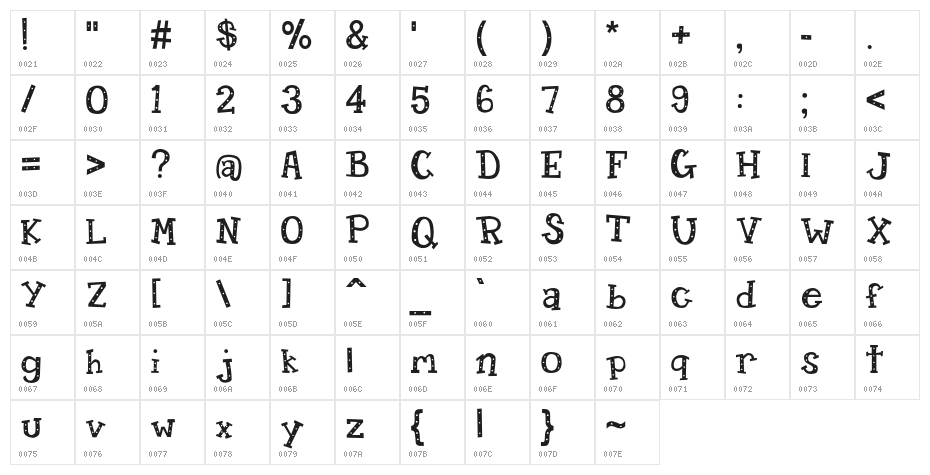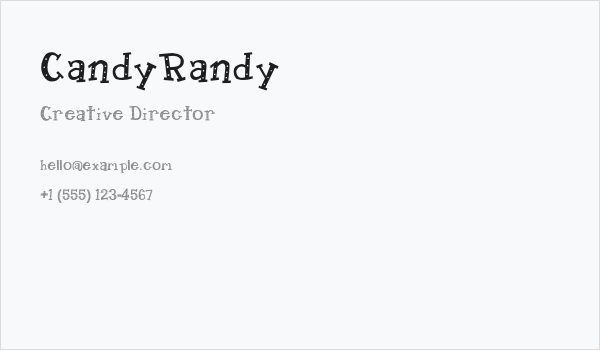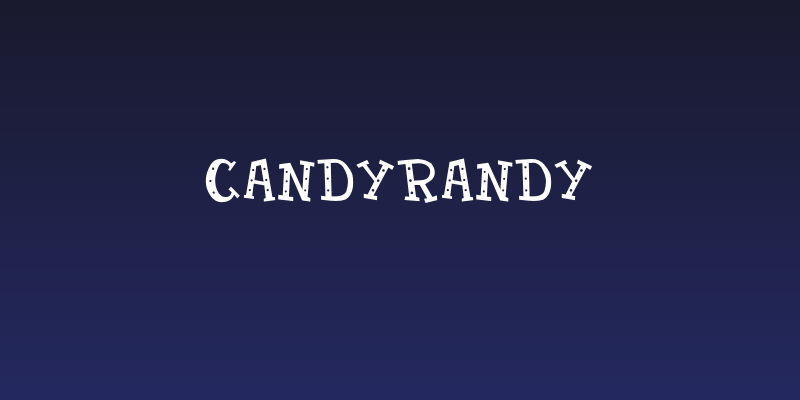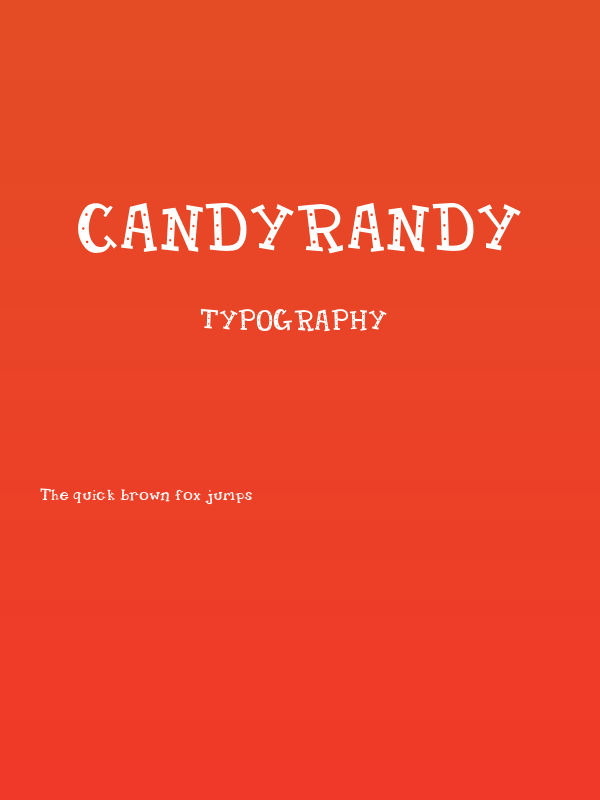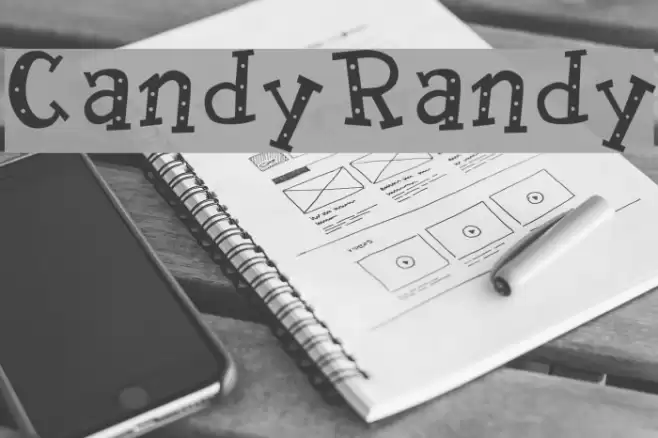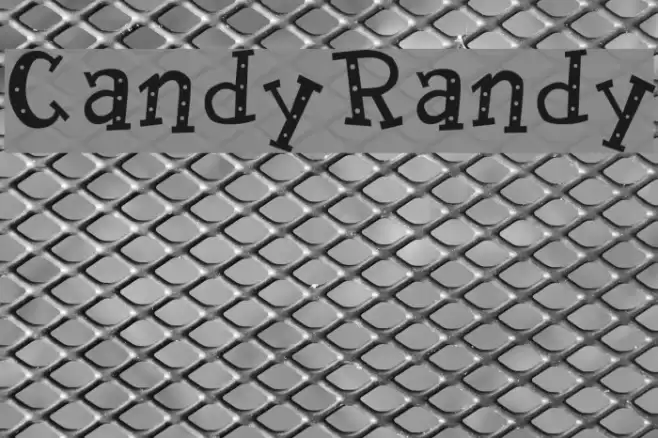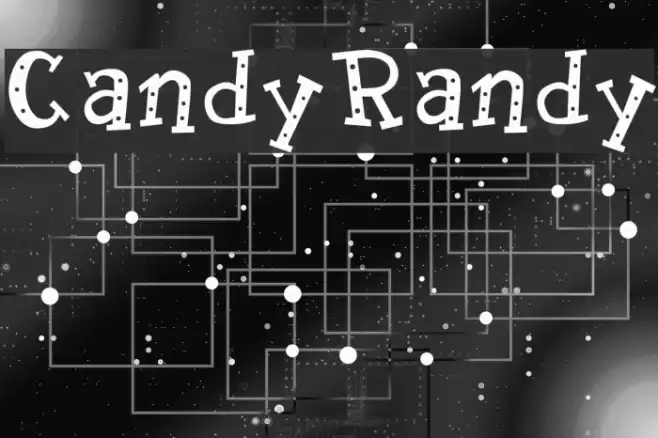
CandyRandy Font
| Категория | Cartoon |
| Общий стиль | Playful, Whimsical |
| Рекомендуемые проекты | Ideal for children's books, party invitations, playful branding, and festive event posters. |